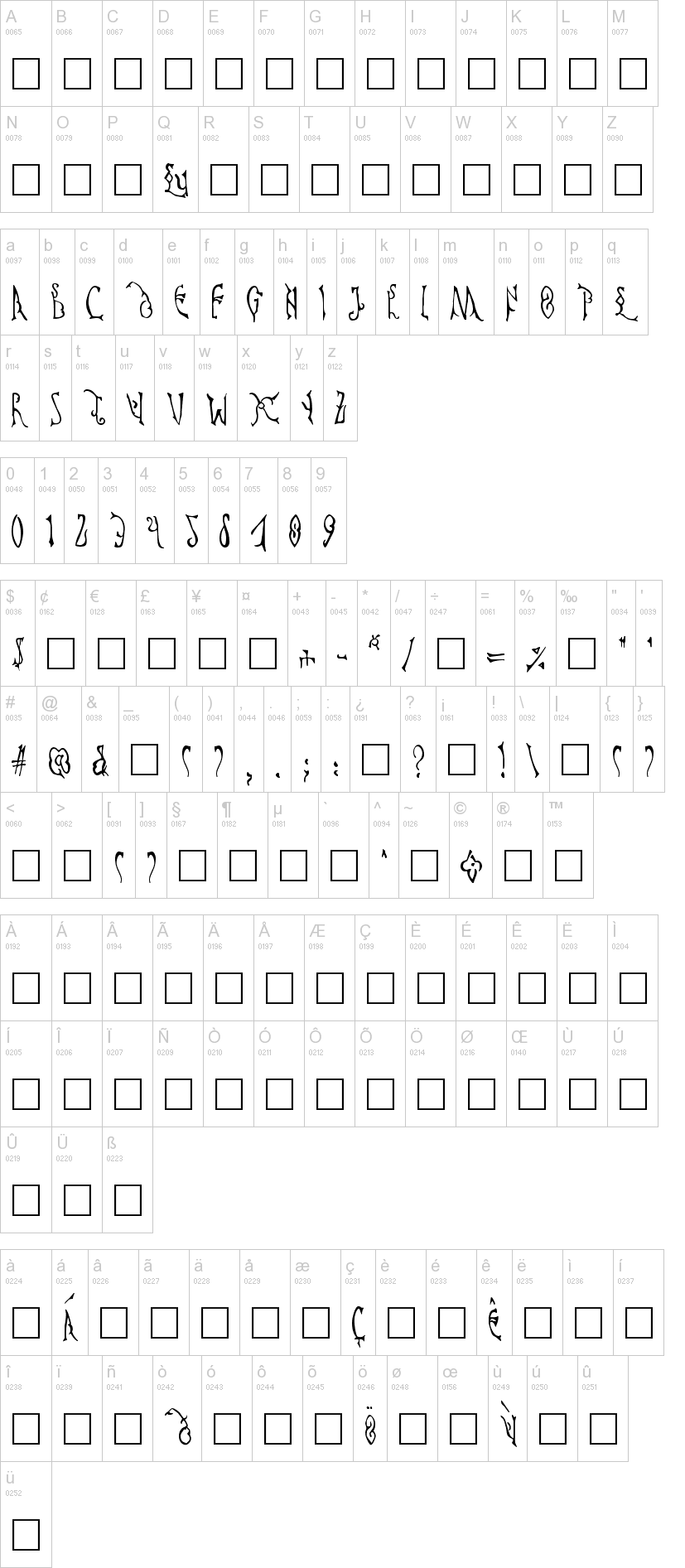
Cyprian(又名:Cypria)是一款具有维多利亚时期风格的欧洲字体,它的字体特点是具有细腻的花纹和锐利的衬线,整体显得非常精致优雅。它可以用于制作海报、广告、书籍封面等等,可以给视觉效果带来更多的精致和优雅。内容介绍
Cyprian是一款非常不错的手写艺术字体,具有很好的视觉感,适合于文化类的宣传设计、商业类品牌的广告和产品包装设计以及个性化文字排版等较多场景。